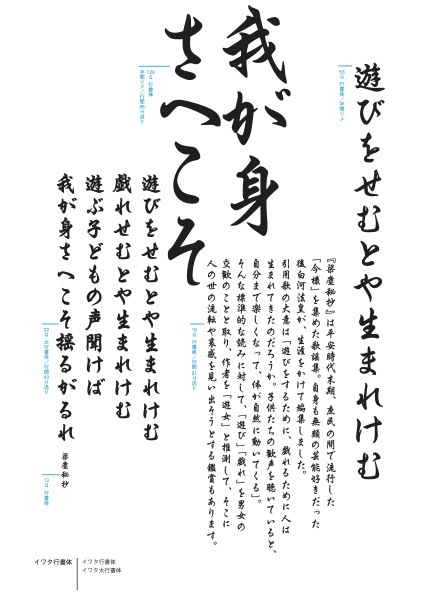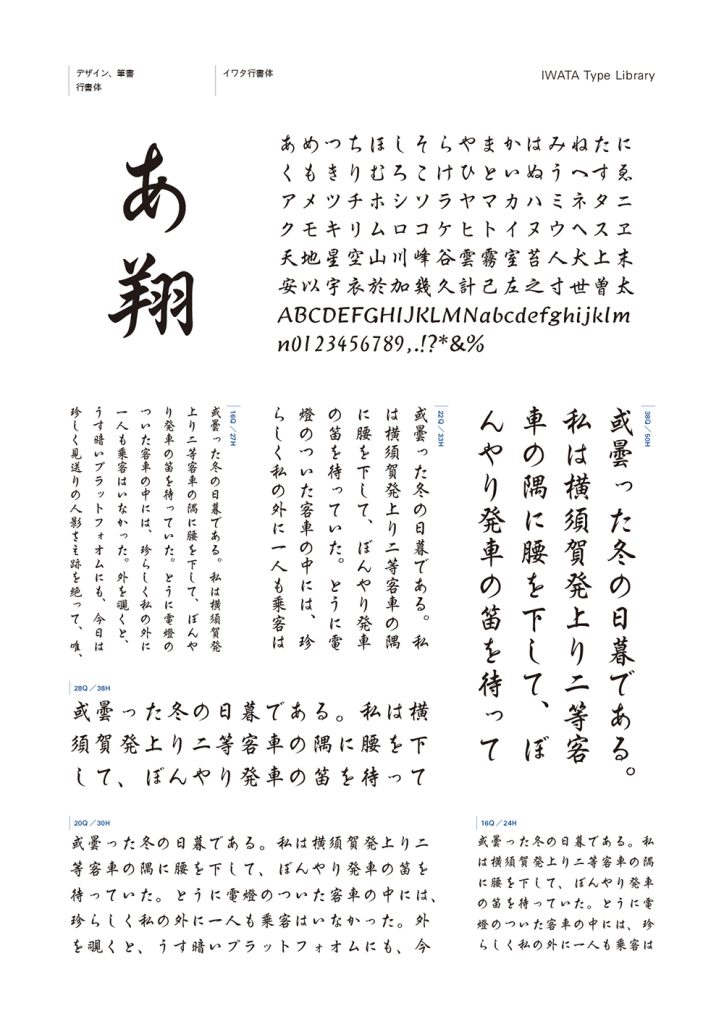
行書体
イワタ行書体
イワタ太行書体
楷書と草書の中間に位置する書体で、読みやすさと書きやすさを兼ね備えたデザインが特徴の筆書系書体です。
字画の省略が過度にならず、文字の美しさと可読性を保ちながらも、適度に流れるような筆運びを実現しています。
崩し過ぎず、ほどよく柔らかく、しっかりとしたバランスでデザインされているため、一般的な文章や手書き風の表現に適しています。